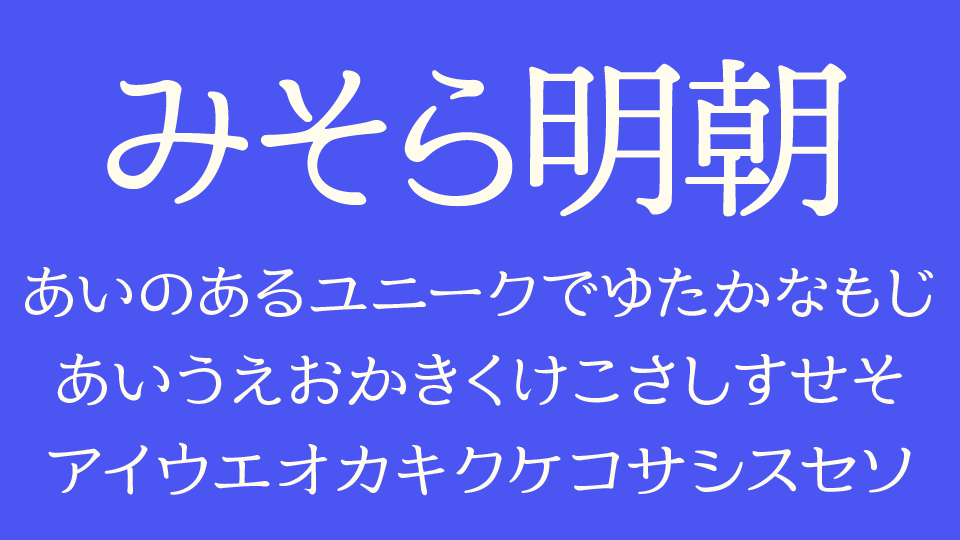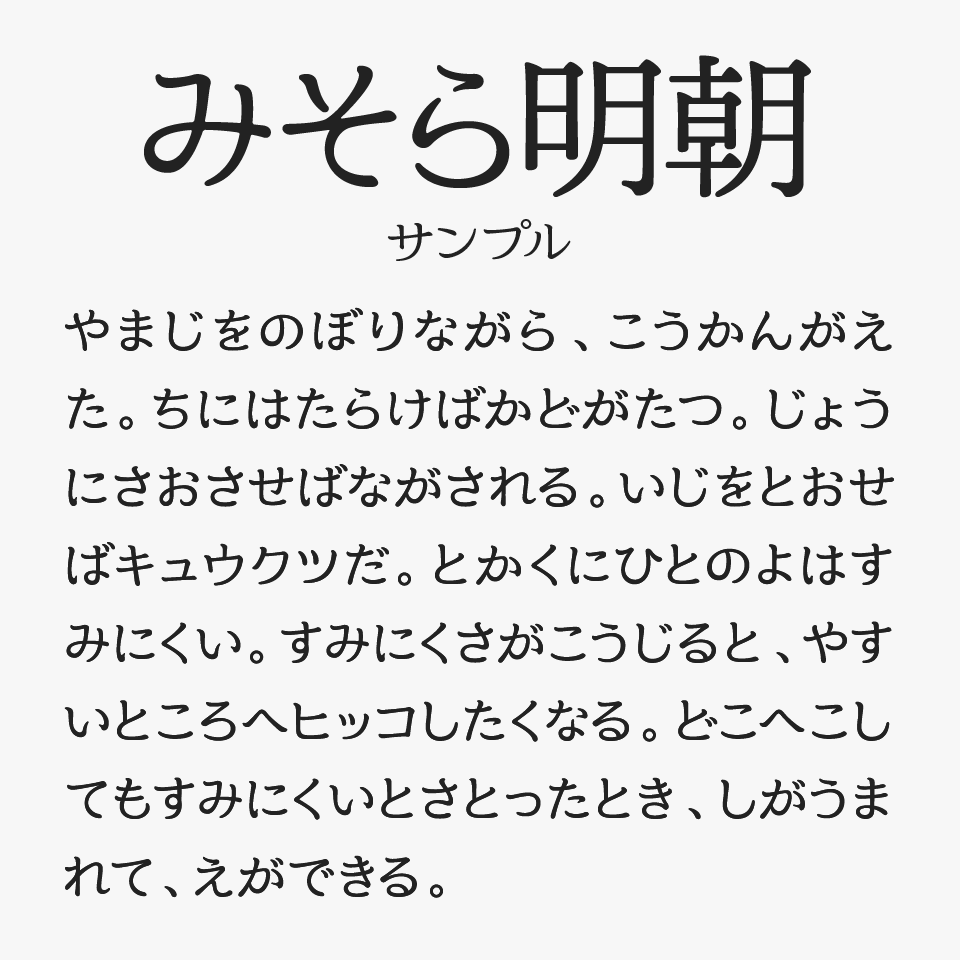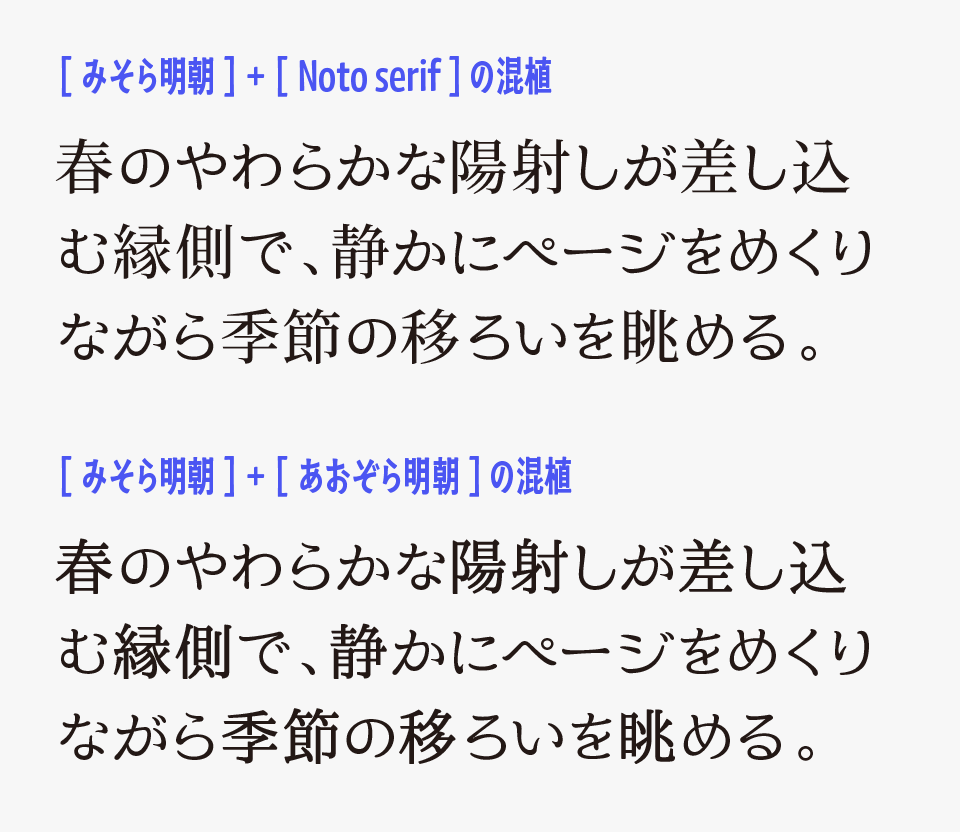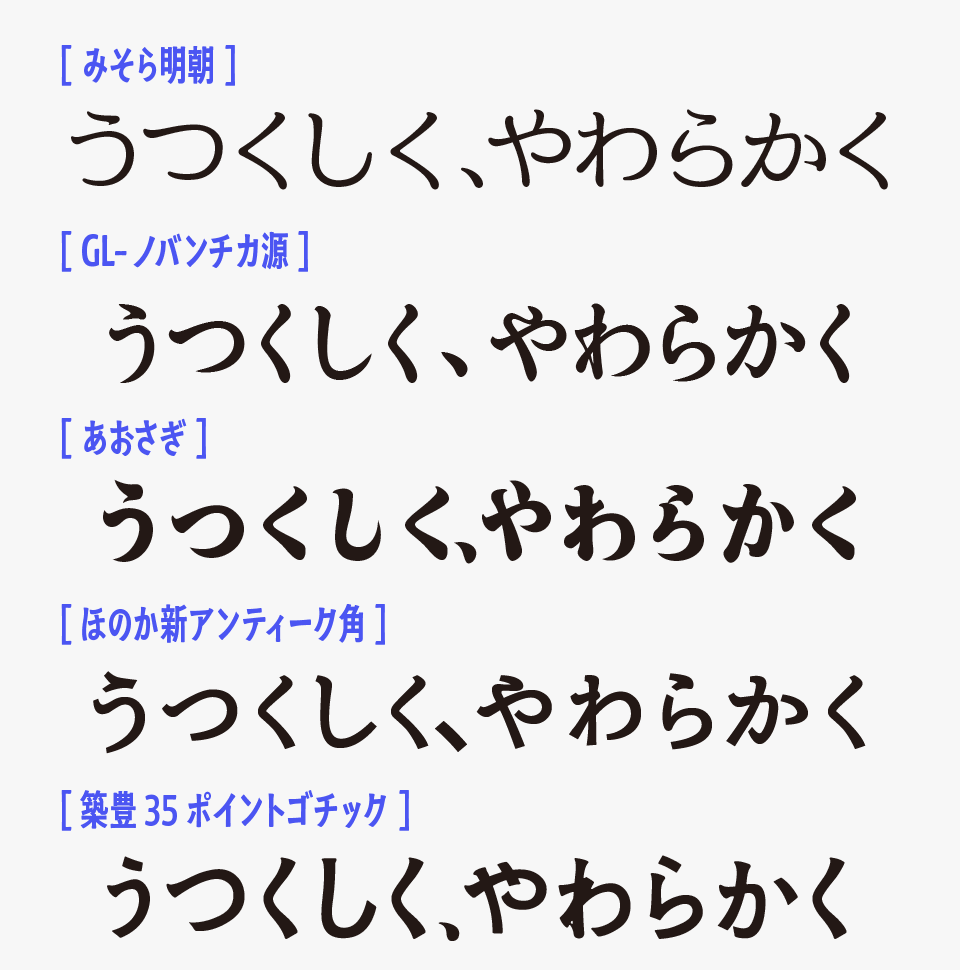
みそら明朝フォントは、「見やすくてかわいい明朝体」をテーマに制作された、やわらかな仮名が可愛らしさと上品さを兼ね備えた明朝体フォントです。
かな文字には丸みを感じる穏やかなクネッといたクセのある曲線が使われており、明朝体らしい上品さや落ち着いた雰囲気を持ちながらも、親しみやすい丸みによって、可愛らしさと読みやすさをバランスよく両立しているフォントです。
みそら明朝
ひらがな・カタカナのみが収録されているフォントのため、漢字を使う場合は、ほかの明朝体フォントと組み合わせて使う必要があります。組み合わせ事例として、「Noto serif」「あおぞら明朝」と混植していますが、他の明朝でも面白いと思うので、ぜひいろいろ試してみてください。
みそら明朝の混植事例
みそら明朝フォントを、ほかの柔らかい明朝体フォントと比較してみると、かな文字の全体的な丸みがあるやわらかさと、筆圧を感じる線先が可愛らしさと親しみやすさが特に際立っています。
比較フォントは、「ノバンチカ源」「あおさぎ」「ほのか新アンティーク角」「築豊35ポイントゴチック」と使用していますが、どれも特徴的な明朝体フォントなので、ぜひあわせてチェックしてみてください。
みそら明朝と、、「ノバンチカ源」「あおさぎ」「ほのか新アンティーク角」「築豊35ポイントゴチック」の比較
収録文字は、ひらがな・カタカナ・ごく一部の約物・記号が収録されています。